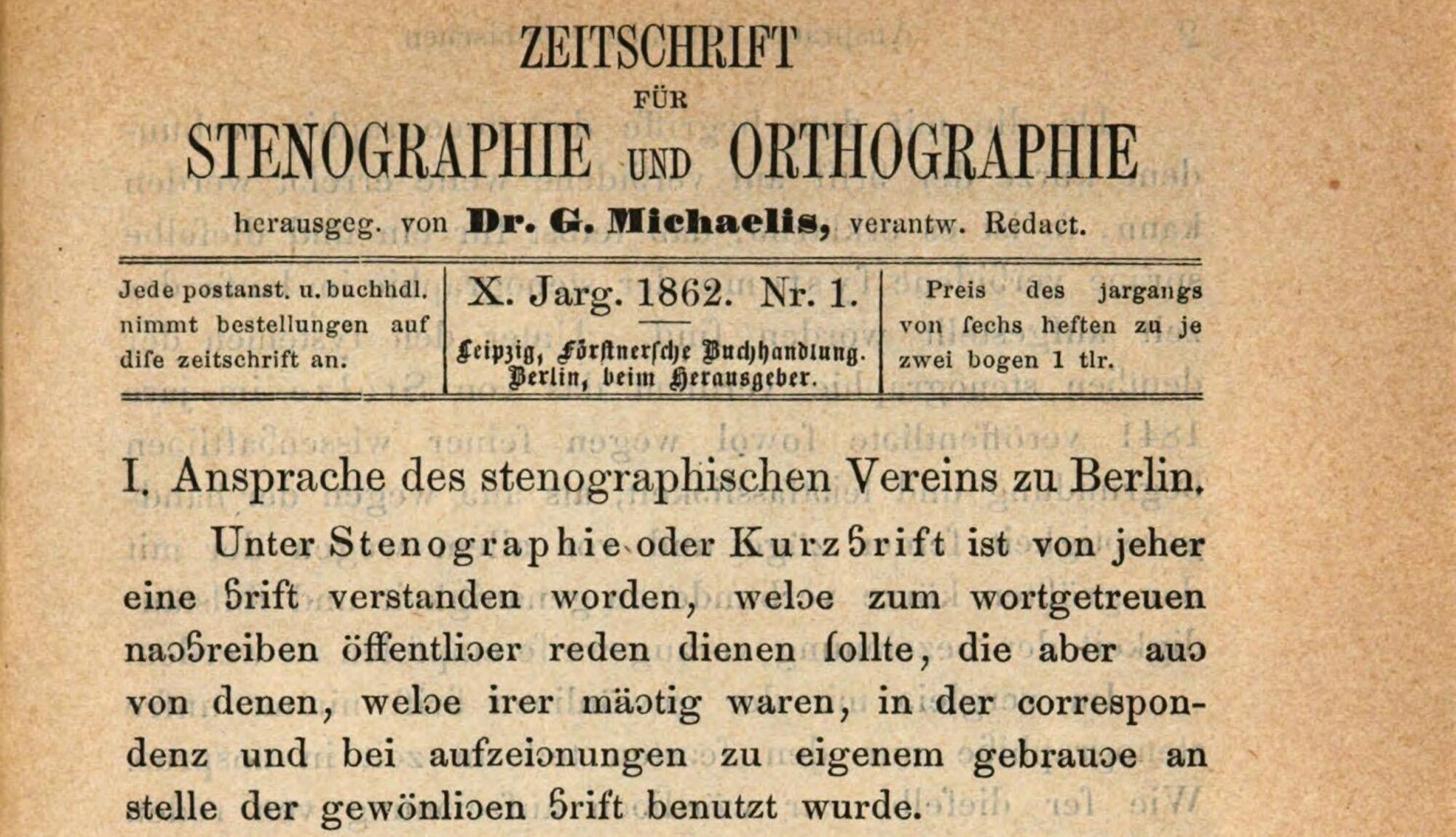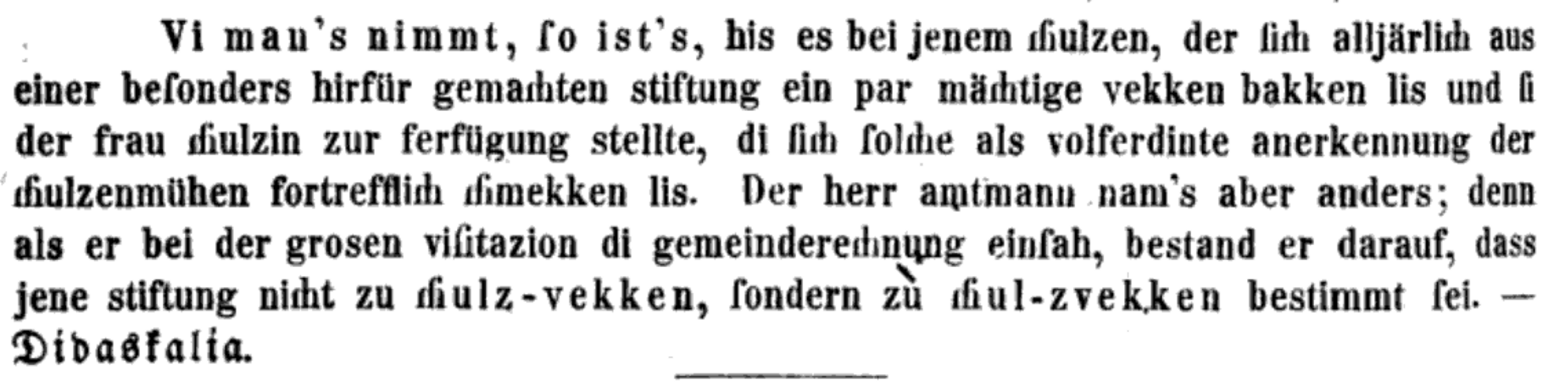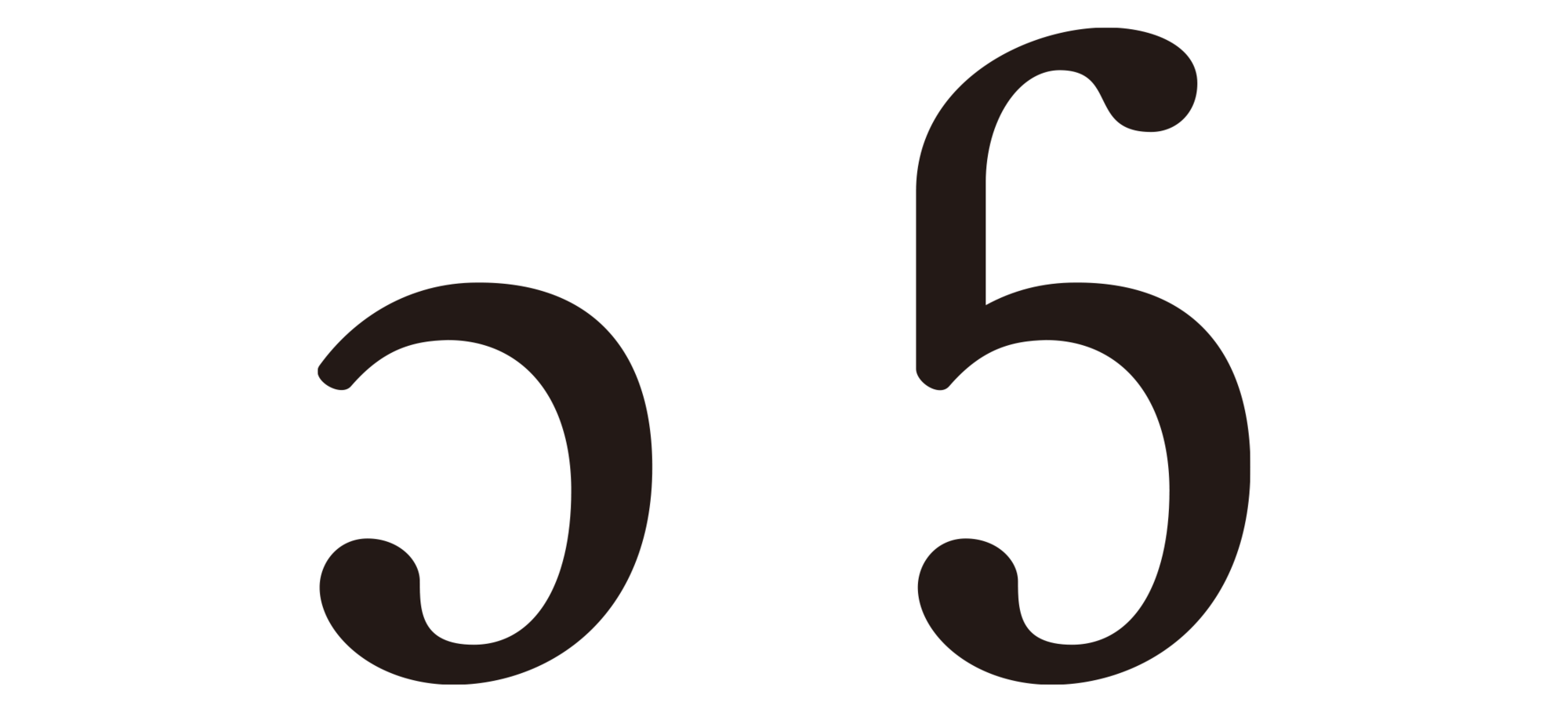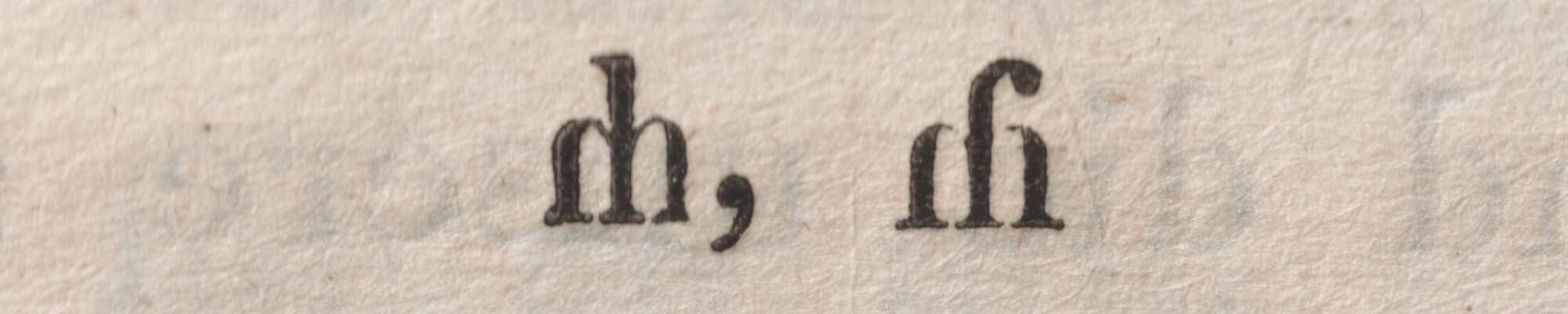
Mitte des 19. Jahrhunderts schlugen Prof. Dr. Gutav Michaëlis und andere Einzelbuchstaben vor, die ch und sch in deutschen Texten ersetzen sollten. Es erschienen auch verschiedene Drucksachen mit entsprechenden, eigens geschnittenen Bleisatzbuchstaben. Eine gute Idee oder übereifriges Reformbestreben? Ein Blick zurück auf eine in Vergessenheit geratene Idee.
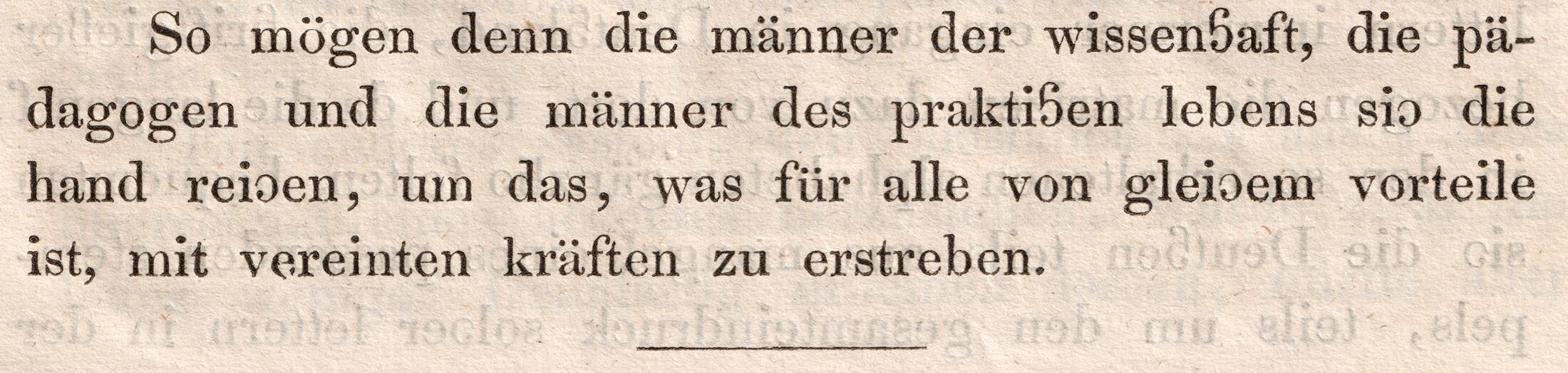
Die genannten Bestrebungen fallen in die Zeit des Deutschen Bundes. Noch herrschte die Kleinstaaterei. Es gab noch keinen deutschen Staat und keine einheitliche Rechtschreibung. Jeder Staat des Bundes konnte seine eigenen Rechtschreibregeln für die Schulen aufstellen, denen dann aber auch wieder abweichende Hausorthografien in Verlagen oder schlicht persönliche Vorlieben von Autoren und Setzern gegenüberstanden. Man konnte sich freilich an die zahlreichen Bücher zur Rechtschreibung und Grammatik (von zum Beispiel Adelung, Campe, Heyse, den Gebrüdern Grimm, Sanders u. s. w.) anlehnen, aber auch sie beschrieben letztlich nur persönliche Vorlieben der betreffenden Autoren ohne jegliche Amtlichkeit oder auch nur die Wirkung eines De-Facto-Standards. »Mich schmerzt es tief gefunden zu haben, dasz kein volk unter allen, die mir bekannt sind, heute seine sprache so barbarisch schreibt wie das deutsche« schrieb Jacob Grimm noch 1847.
Dabei ging es nicht nur um Details der Rechtschreibung. Es tobte auch noch ein grundsätzlicher Richtungsstreit. Jacob Grimm und seine Schüler suchten ihr Heil in historischen Schreibweisen, während die sogenannten Phonetiker einen radikalen Umbau der Schreibung entsprechend der Aussprache wünschten (zum Beispiel »Fi« statt »Vieh«).
Auch das Alphabet und die Satzregeln zur Schreibung deutscher Texte waren noch weit von der heutigen Einheitlichkeit entfernt. Letztere wurde durch die deutsche Zweischriftigkeit zusätzlich erschwert. Gebrochene Schriften blieben oft der Tradition verhaftet und hatten lange kein Ä, Ö, Ü und J und der im 19. Jahrhundert immer wichtiger werdende Antiqua-Satz hatte wiederum die typischen Zeichen des deutschen Fraktursatzes nicht. Das Fehlen von Ligaturen für zum Beispiel ch, ck und tz war für viele noch verschmerzbar, während die Entsprechung des Eszett in Antiqua ein nicht enden wollender Streit werden sollte, der erst Anfang des 20. Jahrhundert endgültig gelöst wurde. Die Ideen von Gustav Michaëlis fallen also in Zeit, in der Reformen noch nötig und auch radikale Änderungen an der Schreibung deutscher Texte durchaus noch möglich waren.
Portrait von Gutav Michaëlis.
Michaëlis wurde 1813 in Magdeburg geboren, studierte beziehungsweise promovierte in Göttingen und Berlin und arbeitete eine Zeit lang als Lehrer. Anschließend widmete er den Rest seines beruflichen Lebens der Stenografie, begleitete aber auch Debatten um die deutsche Rechtschreibung und den deutschen Zeichensatz.
Aus seiner Erfahrung mit der Kurzschrift heraus waren Michaëlis die Schreibungen ch und ſch/sch mit zwei beziehungsweise gar drei Buchstaben für einen Laut verständlicherweise ein Dorn im Auge. In der Publikation »Ueber die Anordnung des Alphabets« aus dem Jahr 1859 schrieb er:
»Die bearbeitung unserer rechtschreibung muss notwendig auf die frage füren, ob es geraten sei, die lücke in unserer buchstabenschrift, welche durch das felen von einfachen zeichen für ch und sch hervortritt, auszufüllen. Theoretisch wird man dise frage bejahen müssen, da kein innerer grund vorligt, warum dise in sich einfachen laute nicht auch einfache zeichen und selbständige namen haben sollten.«
Für den ch-Buchstaben schlug Michaëlis ein um 180 Grad gedrehtes »c« vor – ein Zeichen, welches bereits in der Stenografie nach Stolz im Einsatz war. Für das sch schuf Michaëlis eine neue Form, indem er dem umgedrehten »c« den oberen Teil eines »ſ« aufsetzte. In einer Fließtext-Anwendung stellte sich dies dann folgendermaßen dar:
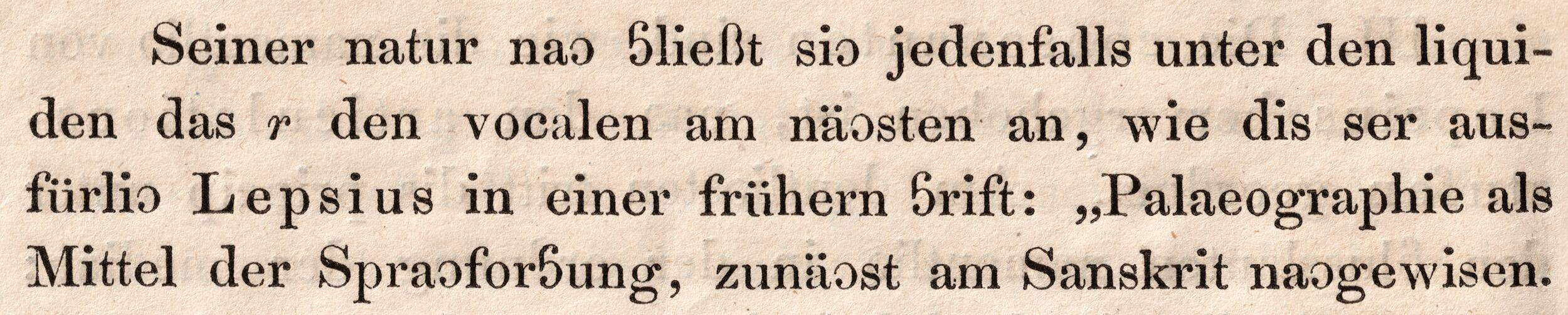
Die Zeichen fügen sich mit ihrem Konstruktionsprinzip recht problemlos in Antiqua-Schriften ein und auch das Lesen der Zeichen funktioniert bei nur kurzer Eingewöhnungszeit überraschend gut. Hätten sich diese Buchstabenformen damals durchgesetzt, würde sie heute wohl niemand infrage stellen.
Auch der Dichter und Publizist Max Moltke schlug eigene Formen für ch und sch vor und benutzte sie in der Mitte des 19. Jahrhunderts in seiner Publikation »Sprachwart« für Antiqua-Texte.
Beispielanwendung im Deutschen Sprachwart, 1857 (Digitalisat)
Der ch-Buchstabe war dabei nah an der bereits in gebrochenen Schriften etablierten ch-Ligatur und damit ohne viel Mühe lesbar. Für die sch-Form wurde ein nach rechts laufender Bogen wie im langen s (ſ) verwendet. Diese Formen wurden auch von Michaëlis besprochen. Er lehnt sie jedoch wegen des Ligatur-Charakters ab:
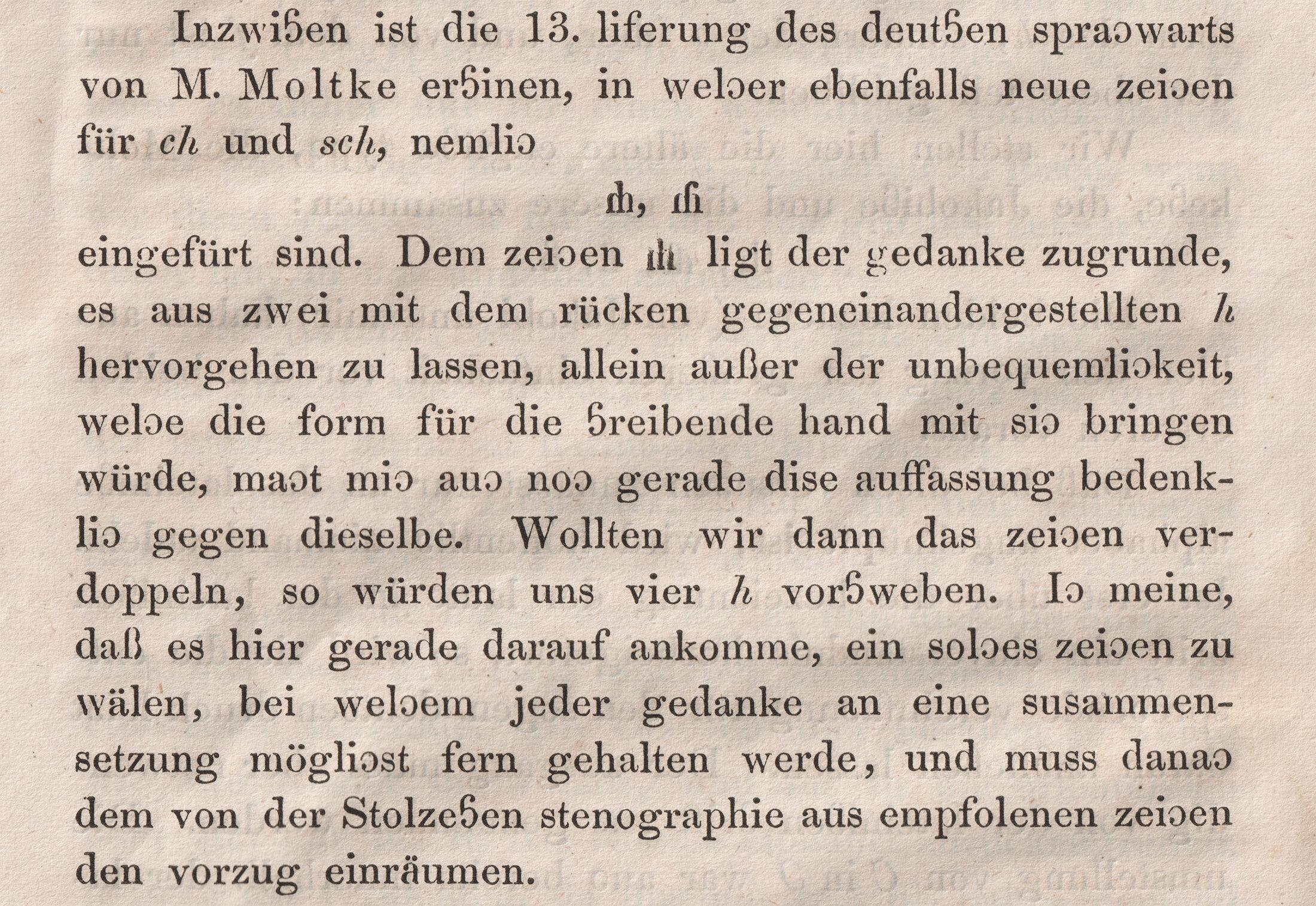
In der Argumentation für seine Zeichen weist Michaëlis vor allem auf das Einsparpotenzial hin. »Von besonderer bedeutung für mich ist die ersparung beim drucke.« Michaëlis lässt sich dies auch durch ein Gutachten der Buchdruckerei und Schriftgießerei Gebrüder Fickert in Berlin bestätigen: »Im allgemeinen würde die einfürung diser beiden zeichen von praktischem vorteile für die buchdruckerei, resp. schriftsetzerei sein, da die im satz vorkommenden ch und sch auf einfache zeichen reducirt werden, wodurch der satz nicht unbedeutend beschleunigt werden würde. Berlin, den 7. Dec. 1857.«
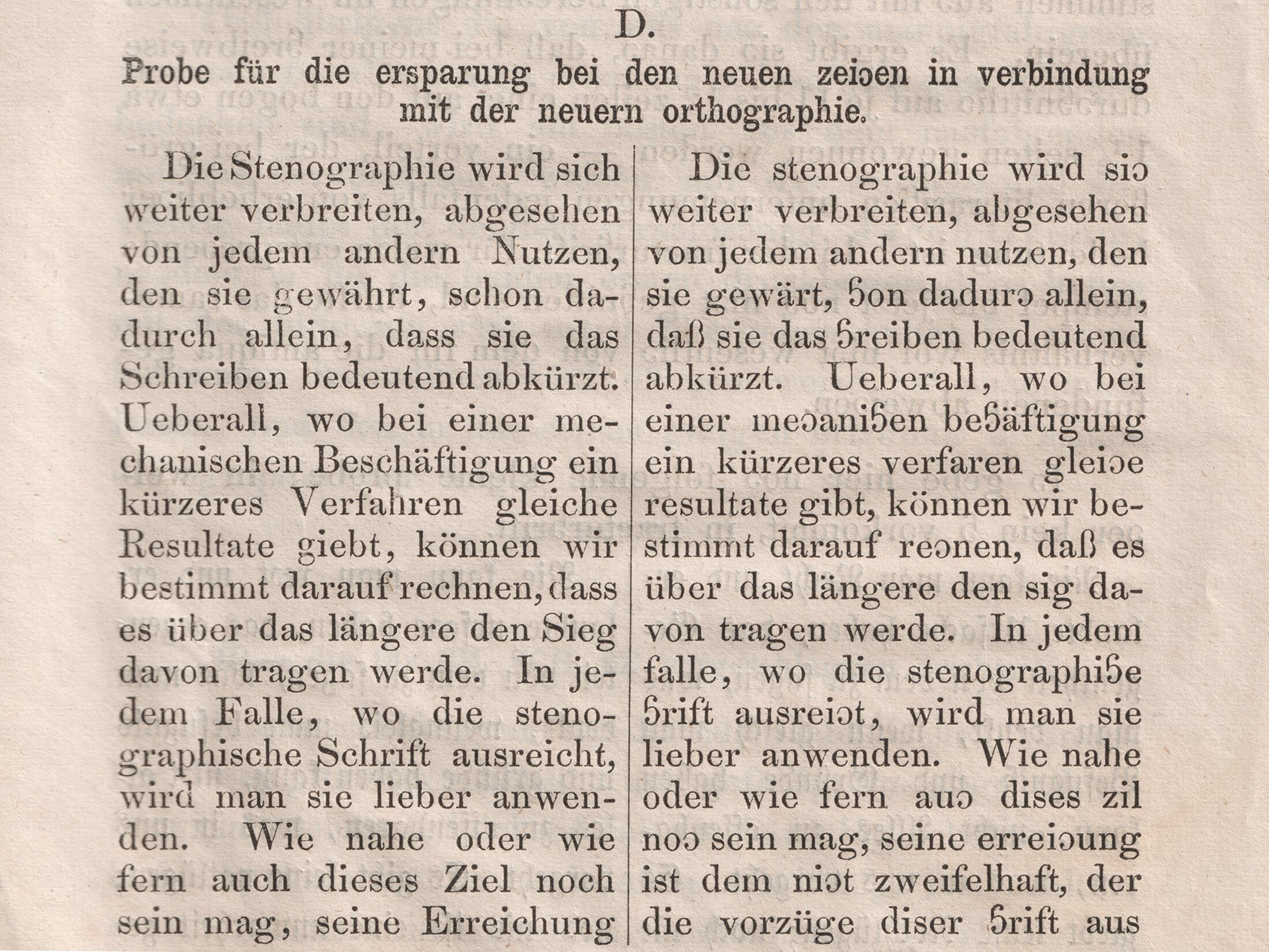
Satzvergleich: ohne (links) und mit (rechts) Anwendung der neuen Schriftzeichen. Hinweis: der Vergleich unterscheidet aber nicht nur die Anwendung von ch und sch, sondern wendet auch weitere Modernisierungsvorschläge an.
Ein weiteres wohlwollendes Gutachten kam vom Berliner Schriftgießer Ferdinand Theinhard:
»Die von herrn Dr. Michaelis für ch und sch vorgeschlagenen zeichen würden sich ser gut dazu eignen, eine unverkennbare lücke auszufüllen. […] Nach der gewönlichen schreibart sind zur herstellung des lautes von ch zwei, zur herstellung des lautes von sch drei buchstaben oder typen erforderlich; sobald an deren stelle einfache, selbständige zeichen träten, würden nach der berechnung der typenzal zur herstellung eines gedruckten werkes 5 bis 6 % an typen weniger zu setzen sein, wodurch sich, namentlich mit rücksicht auf die breite der typen, eine ersparung von etwa einer octavseite auf den bogen ergeben würde. Bei einem werke in dem umfange des Brockhausischen Conversationslexikons würde dis allein schon einen vollen band betragen.«
In den 1870er-Jahren begleitete Gustav Michaëlis übrigens die Versuche zur Etablierung der ersten einheitlichen deutschen Rechtschreibung und machte sich als Vorsitzender des Vereins für die deutsche Rechtschreibung in Berlin für die Etablierung des kleinen und großen Antiqua-Eszett stark. Doch dies ist ein Thema für einen anderen Artikel.